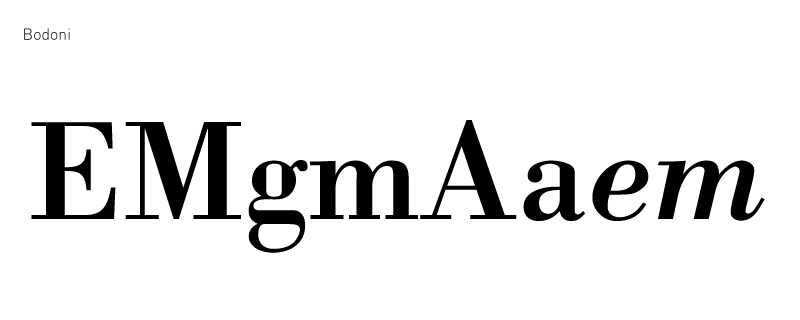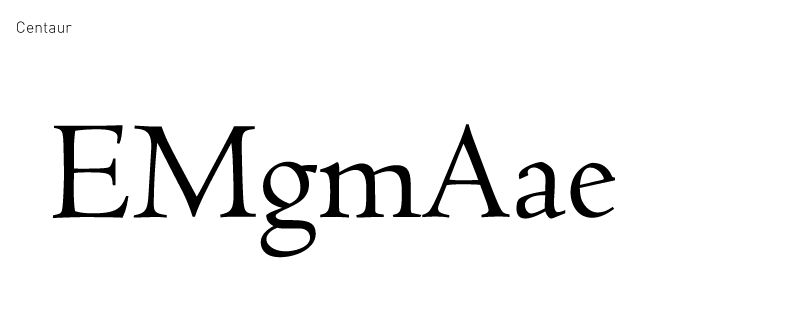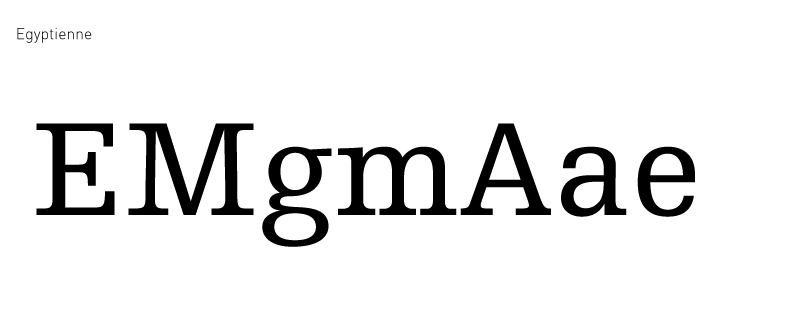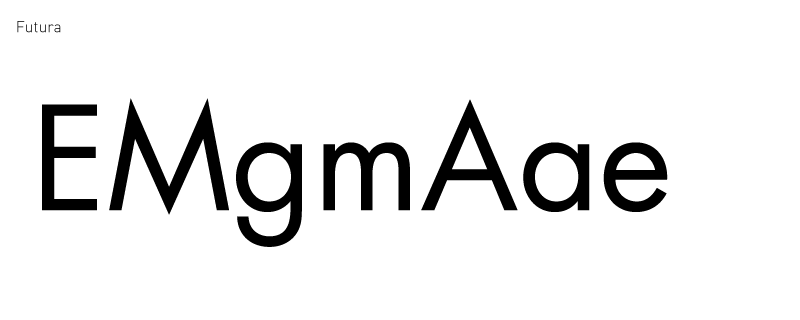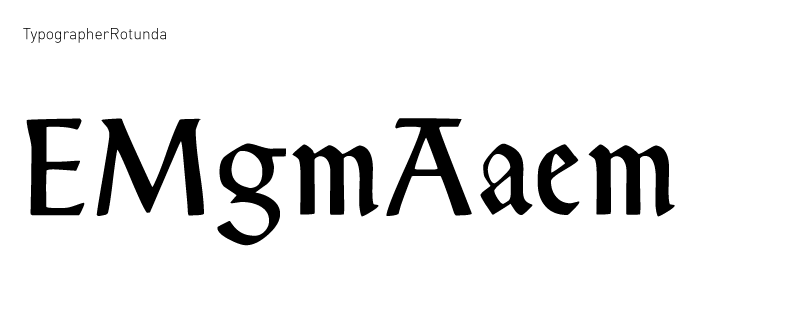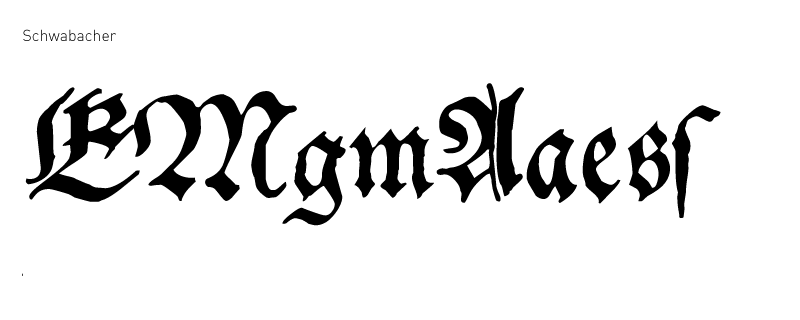
Jan Tschichold nahm 1951 eine Klassifizierung vor, die
einerseits das Ergebnis langer Überlegung und
Analyse ist, andererseits mit der veralteten, irreführenden
Terminologie aufräumt und sie ersetzt. Seine
Aufmerksamkeit widmete er auch den gebrochenen
Schriften, die nicht selten oberflächlich als
„deutsche Schriften“ bezeichnet worden sind.
Die Klassifizierung Tschicholds war für spätere
Einordnungen von großer Bedeutung.
Runde Schriften (römischer Form)
Mit wechselnden dicken und dünnen
Strichen
Schräger Druck
Venezianische Antiqua
Centaur
1470-1500*
Ältere Antiqua, mit Kursiv
Garamond
1495-1757
Vermittelter senkrechter Druck
Antiqua des Übergangsstils, mit Kursiv
Baskerville
1757-1790
Unvermittelter senkrechter Druck
Jüngere Antiqua, mit Kursiv
Bodoni
1790*-1900*
Mit gleichstarken Strichen
Ohne Endstriche
Grotesk
Futura
Seit 1832
Grotesk-Kursiv
Futura italic
Mit Endstrichen
Egyptienne
Seit 1815*
Gebrochene Schriften
Obere Absätze von gebrochen, Rundungen
wie in der karolingischen Minuskel; mit
Neigung zur Brechung, aber ohne scharfe
Spitzen
Rundgotisch (Rotunda)
Gotische Schriften
Typographer Rotunda
Seit 1486
Fast alle Teile der Gemeinen gebrochen
Textur